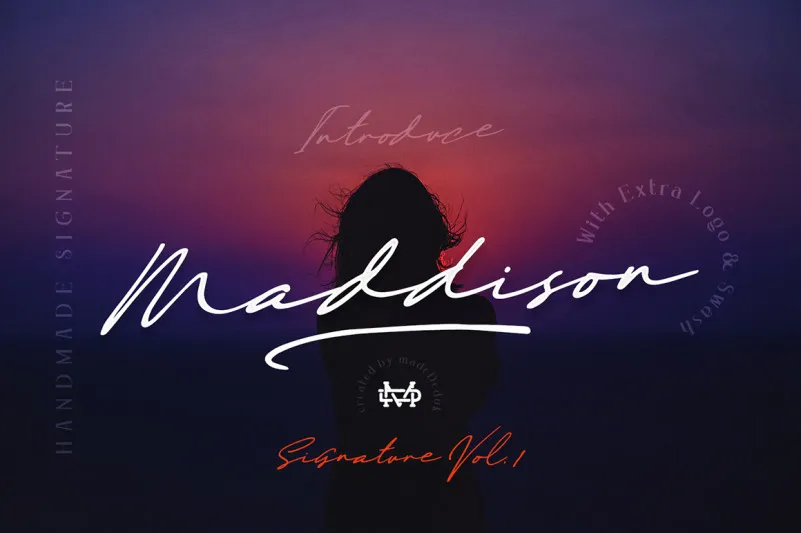
Maddison Signature Font – Fonte Grátis
Maddison Signature Font
Introduzimos a Maddison, uma linda fonte de assinatura elaborada à mão. Esta fonte é perfeita para criar designs com um toque natural e único. Com mais de 170 ligaturas, você pode criar textos incrivelmente profissionais sem precisar usar ferramentas de edição complexas. A Maddison Signature Font é ideal para uso em posters, capas de livros, materiais promocionais, campanhas de moda, newsletters, identidades corporativas, anúncios, revistas, cartões de agradecimento e capas de álbuns. Também pode ser usada para designs que incluem frases únicas ou citações. A Maddison Signature Font é uma adição imprescindível para qualquer designer que busque um toque pessoal em seus projetos.